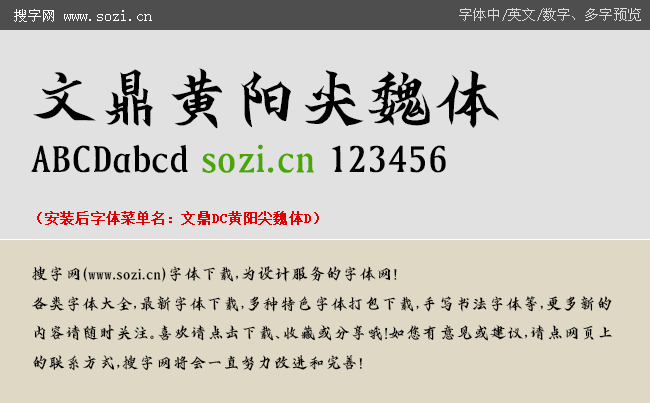
文鼎黃陽(yáng)尖魏體
搜字網(wǎng)提供一款文鼎黃陽(yáng)尖魏體中文字體下載,文鼎黃陽(yáng)尖魏體書(shū)法字體在形體上彰顯了獨(dú)特的風(fēng)格,挺勁犀利,轉(zhuǎn)折剛健雄強(qiáng),具有現(xiàn)代時(shí)尚感,融合了魏碑體、瘦金體、行書(shū)和裝飾體等多元要素,是一個(gè)融合藝術(shù)性、創(chuàng)新性和經(jīng)典性的書(shū)法字體?梢詰(yīng)用于美術(shù)設(shè)計(jì)、宣傳海報(bào)、書(shū)籍設(shè)計(jì)等領(lǐng)域。